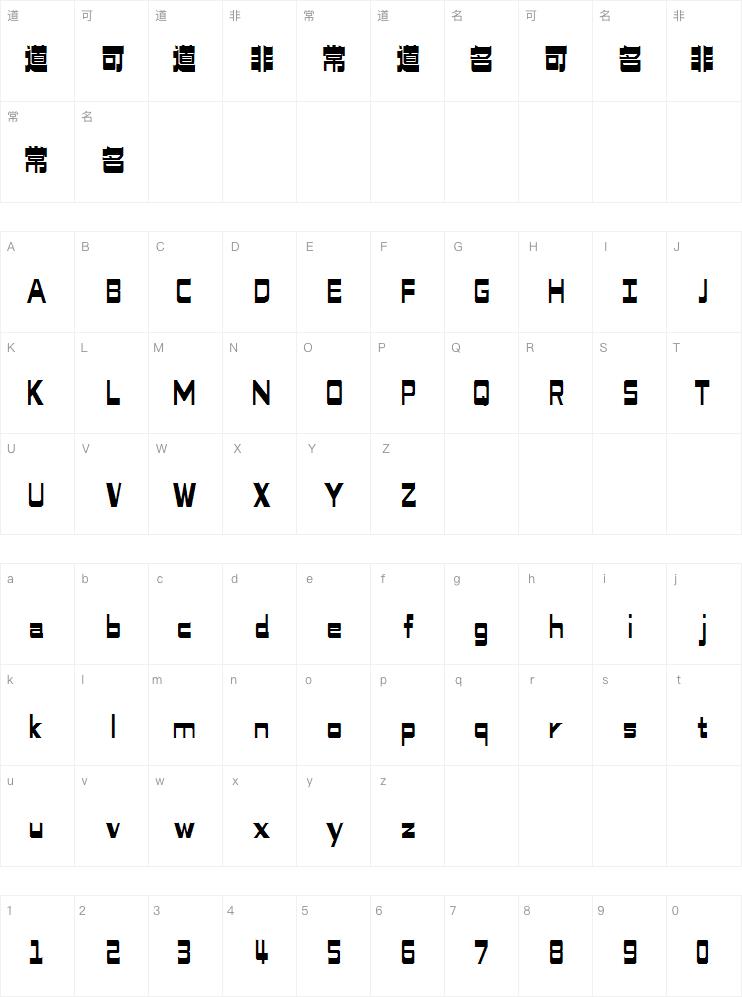
山海摩卡黑w
山海摩卡黑,是一款全新的字体,包含汉字9169个,符号200+个。该字体是一款综艺标题黑体字体,是一款具有强劲视觉冲击力的综艺风格标题字体。字形充实填满整个字框,造型硬朗,同时兼顾圆润性。直线与圆弧的笔画构成坚实有力,简洁明了的笔画切角;采用横细竖粗的逆反差设计手法做笔画设计;字形比例按照宽高8:10的比例设计,使得字体显高;同时笔画带有尖角装饰,使得字形带有律动感,带来强有力的视觉冲击效果。该字体在综艺体的基础上做了诸多创新,使得该字体既有着流动的美感,又有着端肃的凝重,在正式用字场合落落大方,在日常使用环境中不失亲切友好,能够在保留综艺体基本特征的基础上更能适应当下时尚潮流的需要,助力各大新产品夺取标题主战场。